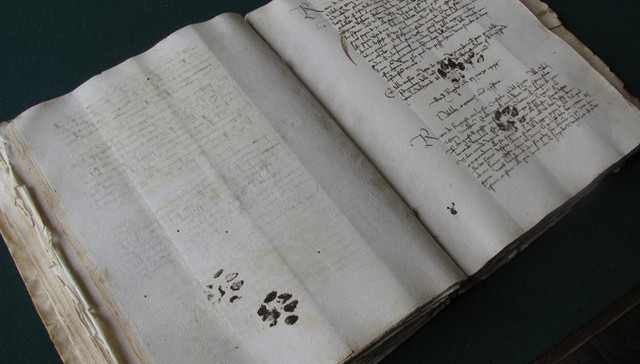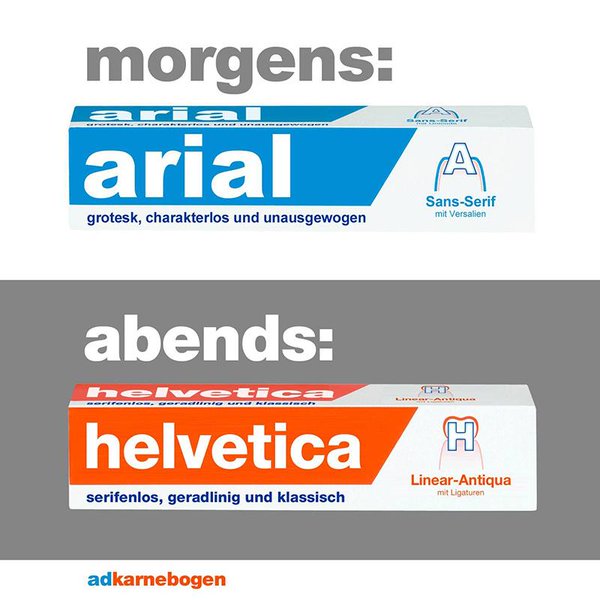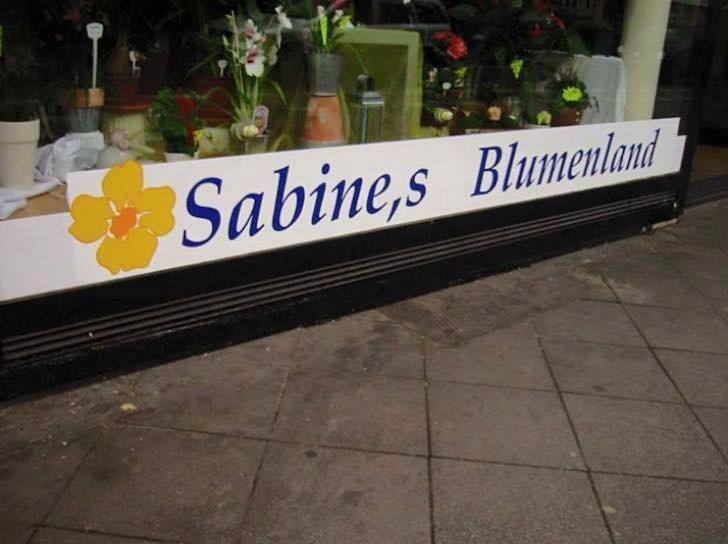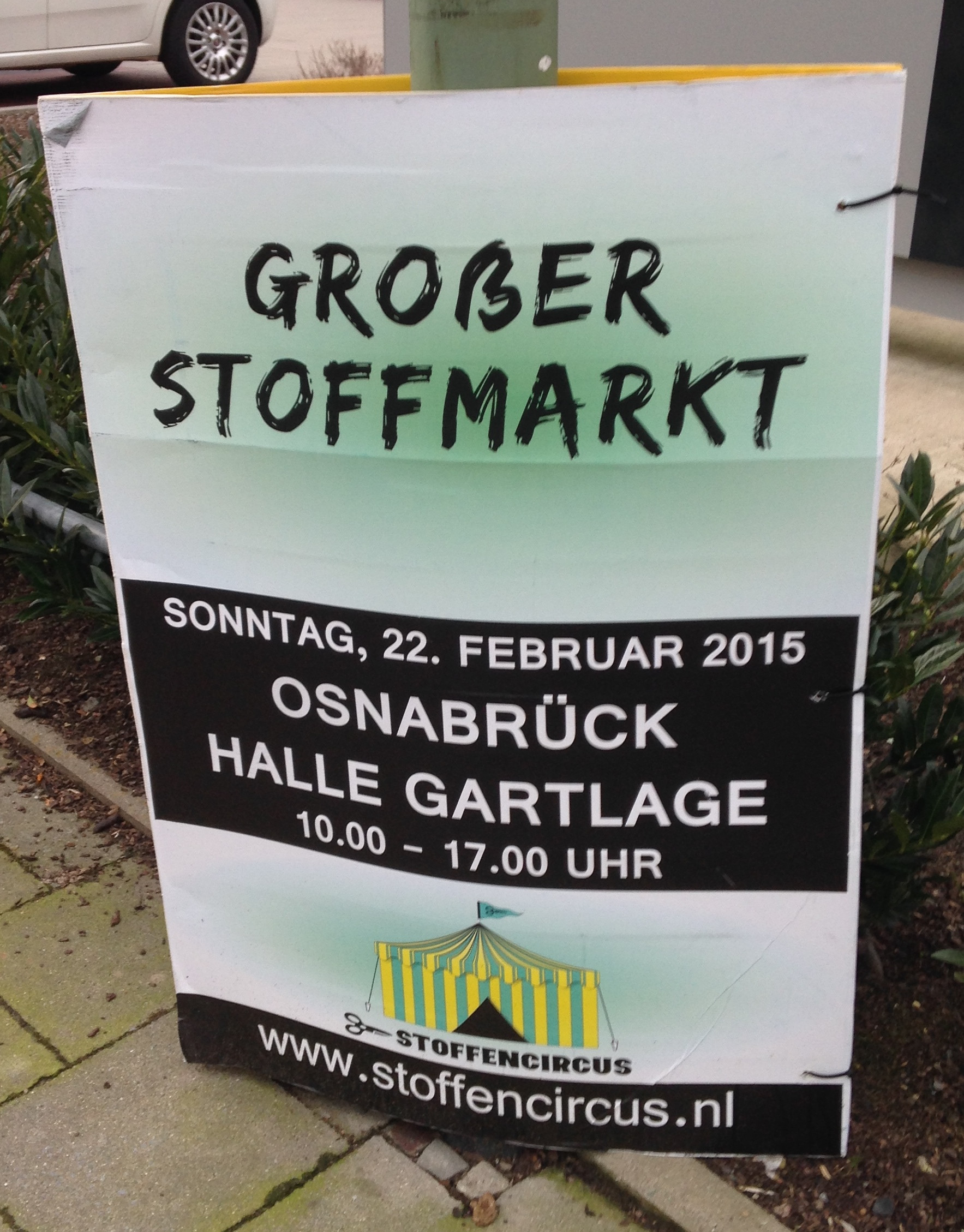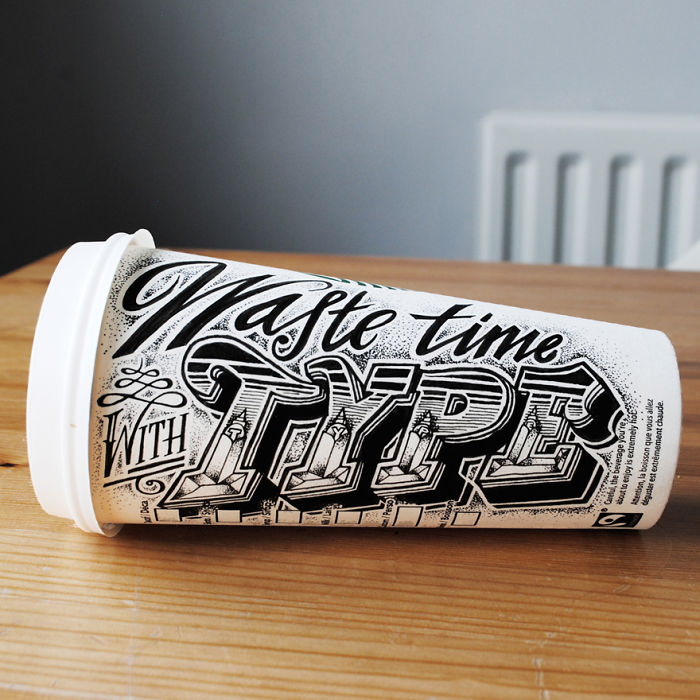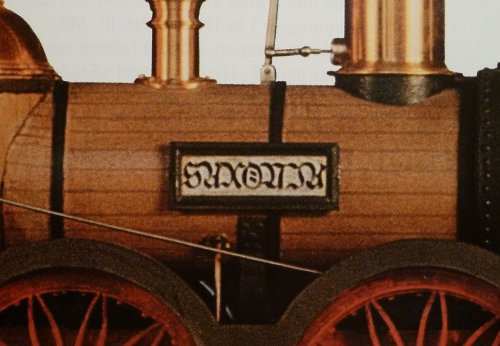
Ja, eben. Wenn Du jetzt die Flinsch-Probe gegen einen Acrylständer eintauschst, hast Du die Genzsch-&-Heyse-Probe übrig und somit ein gutes Geschäft gemacht. Außerdem kannst Du in dem Acrylteil jede Menge Gerümpel unterbringen und hast einen aufgeräumteren Arbeitsplatz. Klassische Win-Win-Win-Konstellation.
Merke: Steht ein Schriftzug unten, muss das Apostroph auch nach unten. Satzzeichen dagegen nach oben und Anführungszeichen werden “umgekehrt„ verwendet :hammer:
Falsch verstanden, das ist 'ne Aufzählung, der nur das Apostroph abhanden gekommen ist, und eigentlich
Sabine, 's Blumenland (das Blumenland)
heißen müsste, denn beide trifft man im Laden an.
… das Apostroph …
Bitte nicht nach Paprika und Gummi jetzt auch noch den Apostroph kastrieren. Man kann es auch übertreiben mit dem Gender-Gedöns.
Hast du denn nebenan gar nix gelernt? ;-)
Echte Caffarelle :-)
Ich hatte auch schon mal starken Filterkaffee in die HP 26 Patrone gefüllt, damit leß ich schönes Wasserzeichen-Papier drucken.
Oder hatte das schon mein Bored-Panda-Co-Botschafter gepostet?
Nö … der hat das noch nicht entdeckt, weil er Besuch hatte und sich seine zeit zur Abwechslung mal nicht im Netz vertrieben hat ;-)
Wer sich hier noch fragte, ob ein a verunglückt ist ...
... wird spätestens einen Eingang später aufgeklärt ...
... leider gibt's keinen weiteren 44er Eingang ...
Gab es sowas häufiger, dass mit griechischen Buchstaben numeriert wird?
Wo ist das denn? Vielleicht kennt Phoibos diesen Ort und kann uns erklären, das dieser zwischen 19 v.Chr. und 276 n.Chr. unter griechischer Herrschaft stand und deswegen traditionell griechisch Unternummeriert wird. :hammer:
Ich hab neulich auch noch was gefunden:
Hat mich gefreut, das auf so einem vermeintlichen Billig-Plakat zu sehen, das auch noch aus den NL kommt, wo das Ringel-S nichtmal benutzt wird …
Wo ist das denn?
Καρλσρούη
Ach deswegen ... ;-)
Vielleicht gehört das Haus auch nur einem Altphilologen, der damit dem Trend zum Aussterben der Altsprachenkenntnisse entgegenwirken wollte. Die Tragik der Altsprachenscene zeigt sich besonders darin, daß man damit nicht genug Geld verdienen kann, um einen Häuserblock zu kaufen, der für das ganze Alphabet gereicht hätte. So bleiben die Kenntnisse Karlsruher Postboten auch fürderhin rudimentär.
*grins* Immerhin hat's zum Kulturdenkmal gereicht ...
So lange die Einwohner dann nicht sagen: ich wohne in Haus vierundvierzig-eszett :hammer:
Google hat immerhin keine Treffer für "Gartenstraße 44ß" ;-)
(Aber auch keinen für "Gartenstr. 44β" ...)
Hier scheint, denke ich, der Schriftgestalter schon vorausgegriffen zu haben und hat in seinen offenbar rein versalen Zeichensatz bereits ein Versaleszett integriert, das dann auf der Belegung vom kleinen Eszett liegt. So zumindest könnte ich es mir denken. Was allerdings immer noch nicht erklärt, warum es auf einem Plakat aus den NL zu sehen ist.
Naja, das Plakat hängt hier in Osnabrück … also das ß gehört da schon hin. Das der Gestalter die Schrift so gemacht hat, kann ich mir auch gut vorstellen …
Jetzt die Frage: Welche Schrift ist das? Die ist nämlich schön! Ich hätte sie gerne für meine Handschriftenliste, jawohl.  :nicken:
Cool! Wirklich nette Schrift. Leider keine Kleinbuchstaben. Aber ich kümmere mich drum, dass die Schrift in meine Liste kommt!  :gimmifive:
So lange es Katzen gibt ...
Eines der seltenen Beispiele des Fraktur-Versalsatzes – und dann scheint auch noch jemand die Buchstaben abgemalt zu haben. Viel Spaß beim Entziffern: